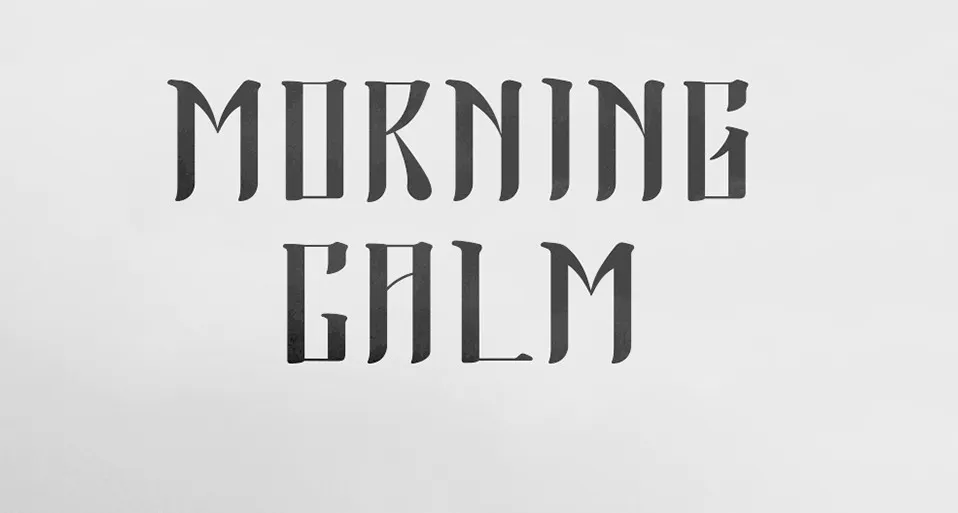
Introduzimos Morning Calm Typeface! Essa fonte foi desenvolvida por Nils Germain, designer proveniente de Seul, Coreia do Sul. Foi criada para seu projeto final na classe de tipografia no Kookmin University. A Morning Calm é uma fonte latina livre inspirada nos post-modernos tipos coreanos e na escrita tradicional coreana a partir da koreana. Suas estruturas modernas, com seus finais de traços muito orgânicos, fazem dela única e bem-adaptável tanto para cabeçalhos quanto para o texto corpo. A Morning Calm é uma opção perfeita para designers que desejam adicionar um toque sofisticado e único a seus projetos visuais.